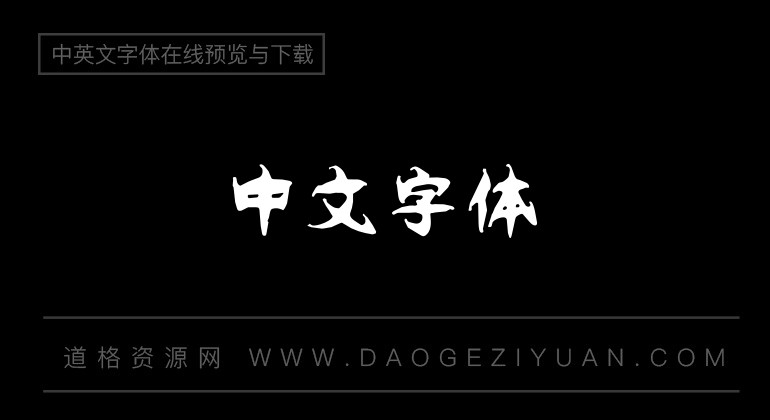
腾祥倩女简
腾祥倩女简是一款楷体字体,由腾祥倩女简创作团队设计,以宋体为基础,利用现代技术将其打造成更加精细、圆润、优美的楷体字体。腾祥倩女简拥有较高的细节处理能力,具有较强的表现力,可以更好地表现文字的精美和细腻。
腾祥倩女简是一款非常不错的手写艺术字体,具有很好的视觉感,适合于文化类的宣传设计、商业类品牌的广告和产品包装设计以及个性化文字排版等较多场景。